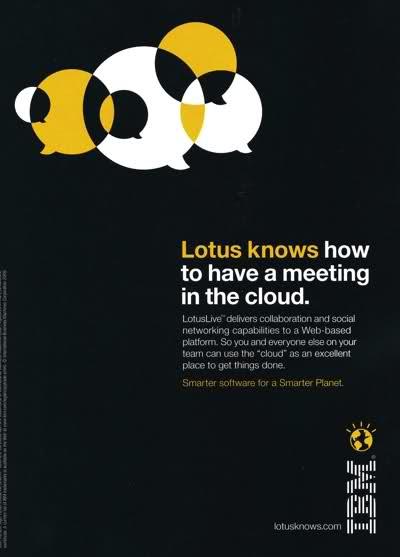
Was für eine Schrift? Lotus knows...
Hallo! Was ist das für eine Font??
Leider hab ich die Ad nicht größer... schaut aus wie Helvetica Neue, aber ich habe keine Ahnung. Danke!
Die Alte? verstehe ich nicht- die ist auf meinem mac als true type Sytemschrift fest installiert, allerdings nur als regular und bold © Linotype 1981- Apple / ( Type Solutions 1990©. Alte Compressed, Condensed und Rounded-Schnitte sind noch als Post Script auf meinem Rechner, '85-'87 © von Adobe. Dan gibt es noch massig Linotype's Neue, ab '81- '93 , ab '88-'93 von Adobe (true type) und noch eine Berthold Häufchen True Types Neue (übrigens identisch mit den anderen Neuen. Hübsch gell.... sonst noch was? Ach ja, die LT Gold Edition, da gibt's noch reichlich Helvetikaas, lekker